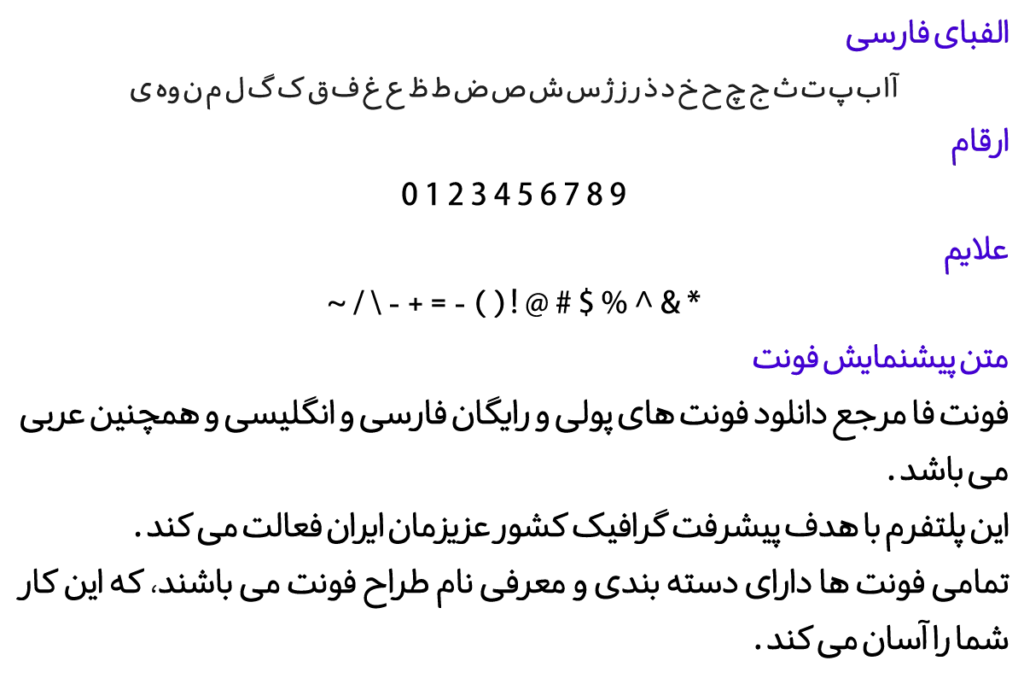
فونت فارسی رایتل – Rightel
طراح فونت: حسین زاهدی نوع فونت: فونت متن
توضیحات و معرفی فونت رایتل
فونت فارسی رایتل ( Rightel ) از مجموعه فونت های آزاد می باشد، همچنین نوع فونت متن می باشد.
فونت فوق العاده زیبای معرفی شده توسط حسین زاهدی طراحی و ساخته شده است.
از این تایپ فیس می توانید در نگارش متن و طراحی های گرافیکی که نیاز به فونت نازک دارد استفاده کنید.